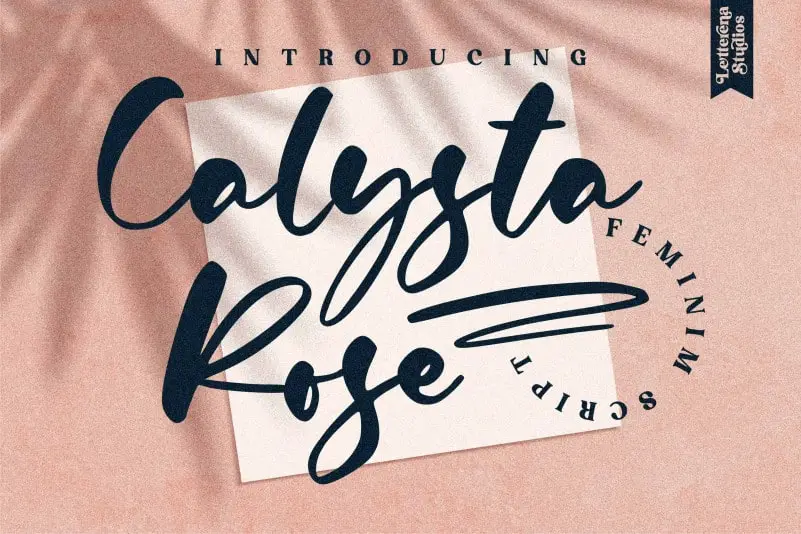
Calysta Rose Script Font – Download Grátis
Calysta Rose Script Font é uma tipografia elegante e encantadora que parece muito adequada para designers que desejam adicionar toques criativos a seu trabalho. Seu charme romântico faz dele uma escolha perfeita para aplicar em itens como convites de casamento, cartões de agradecimento, mensagens pessoais e logotipos. Suas linhas suaves e sua disposição fluida permitem que o texto seja muito delicado ou poderoso, dependendo da situação específica. Calysta Rose Script Font é perfeito para qualquer design visual que exija um toque de escrita à mão, desde cartões de presentes até cartazes de marketing profissional. Sua elegância natural e seu charme sofisticado o tornam uma opção atraente para designers que desejam dar um toque especial aos seus projetos gráficos.